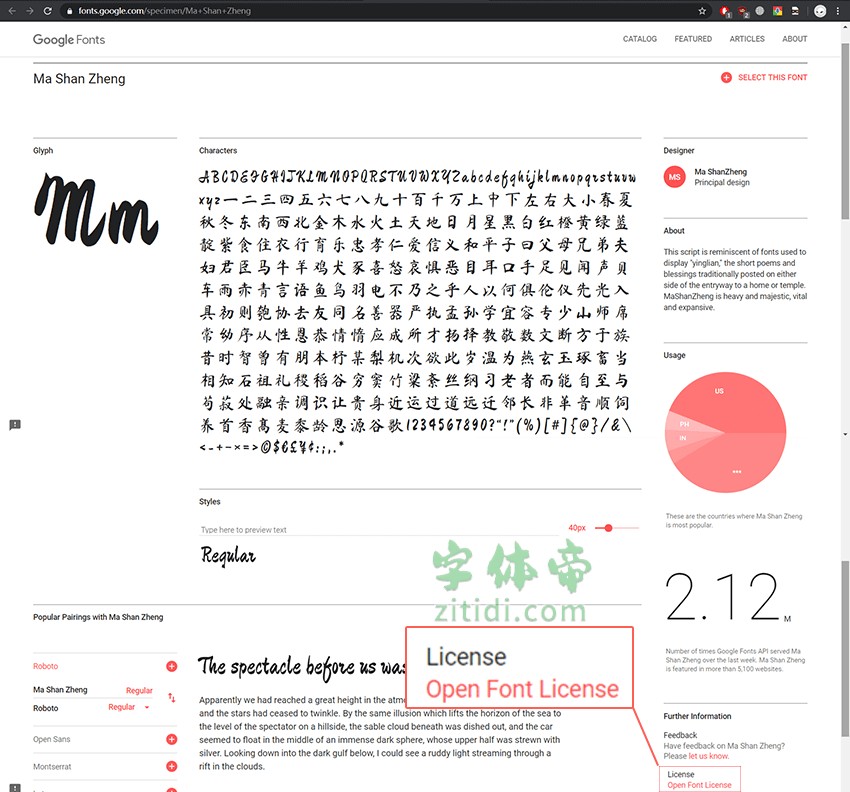
马善政毛笔楷体
字体名称: 马善政毛笔楷体
字体风格: 楷书
马善政毛笔楷书是一款可以免费商用的简体毛笔字体,现在国内可以免费商用的毛笔字型并不多,比较常用的是庞门正道粗书体。现在终于又多了一款马山正毛笔体可以选择,真是太棒了!
马善政毛笔楷体”是一款书写很新颖的字体,字体大方,适合各种设计作品使用!欢迎下载!